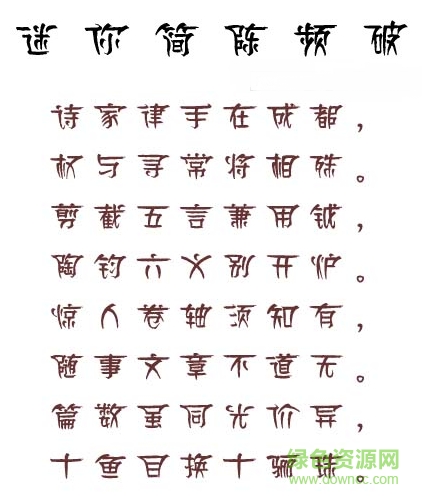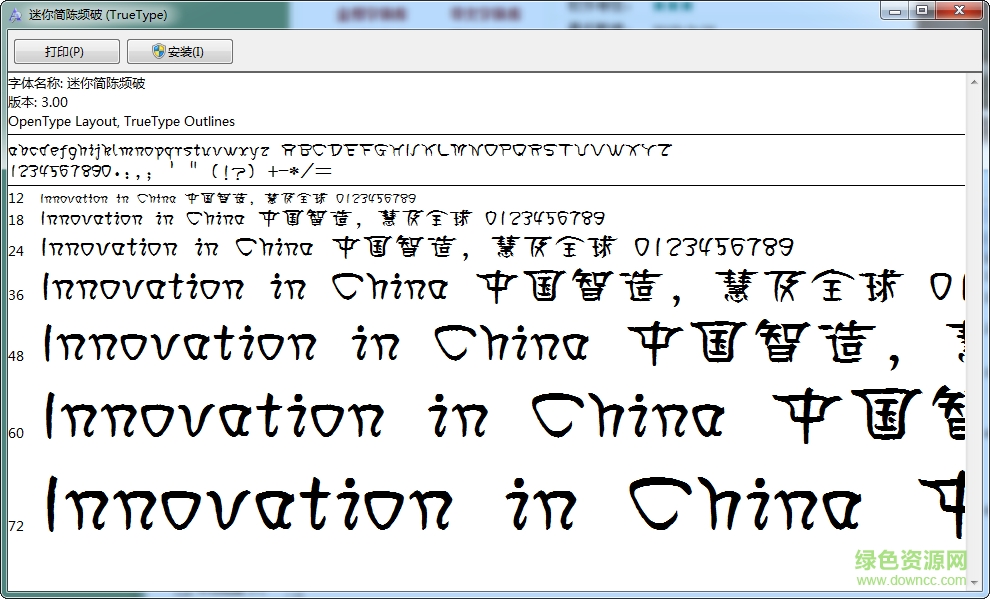
迷你簡陳頻破是一款怪怪體中文簡體字體,字體另類搞怪,奇葩可愛。用來設(shè)計(jì)一些比較卡通畫化的作品。在win7、xp等系統(tǒng)上都可以運(yùn)行使用!喜歡的朋友可以來綠色資源網(wǎng)下載安裝。
迷你簡陳頻破 regular 3.00字體(字體家族名稱:迷你簡陳頻破;字體風(fēng)格樣式名稱:regular),共有7607個字符。
字體家族:迷你簡陳頻破
字體風(fēng)格:Regular
字體版本:3.00
字符數(shù):7607
字形數(shù):8599
字寬:中等(正常